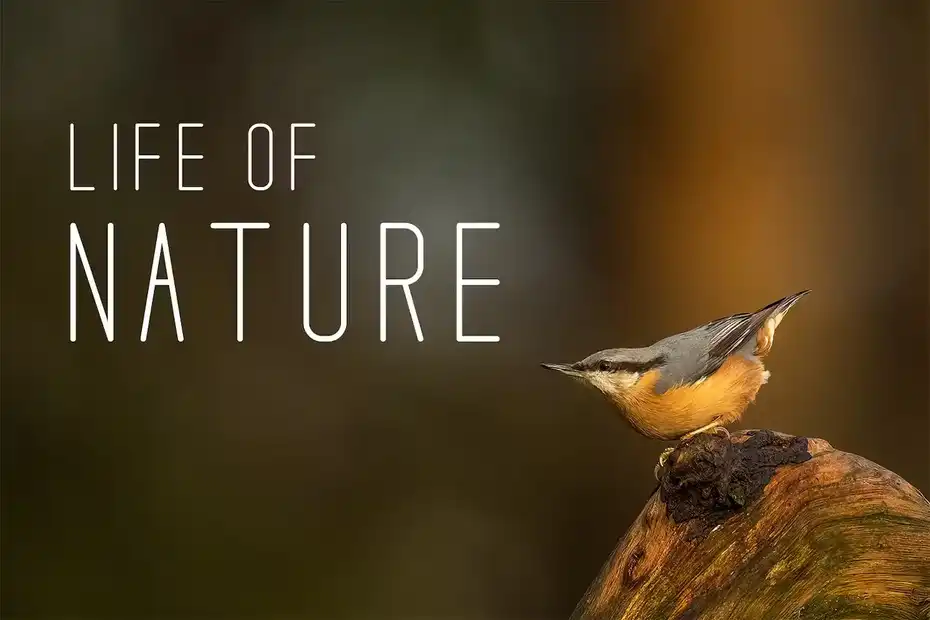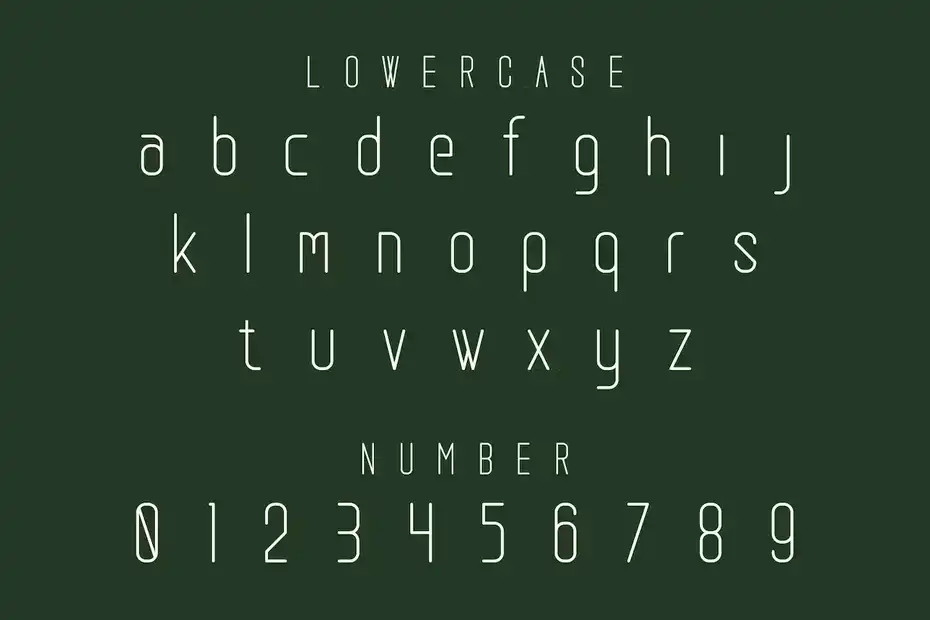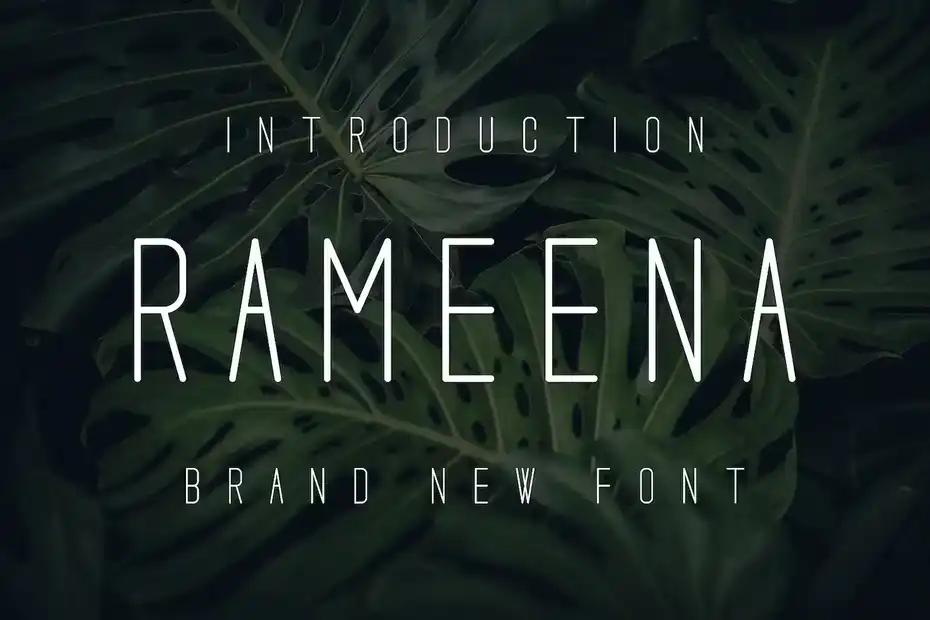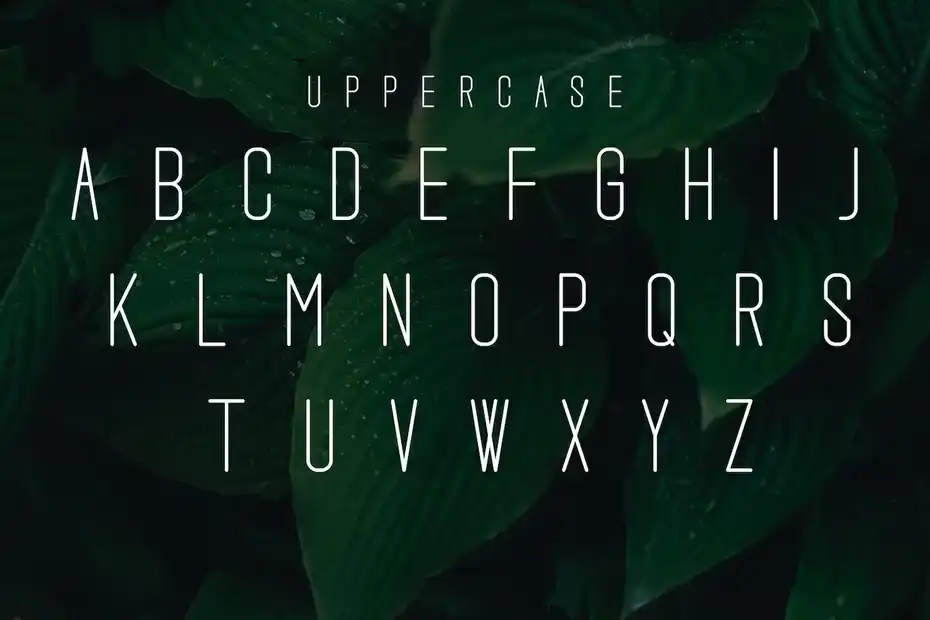
دانلود فونت انگلیسی مدرن Rameena font
فونت انگلیسی مدرن Rameena font : این مجموعه شامل فونت انگلیسی مدرن است که برای کتاب‌ های الکترونیکی، اپلیکیشن موبایل، سرفصل‌، بنر، پوستر، وب‌ سایت‌، مجلات و غیره مناسب میباشد.